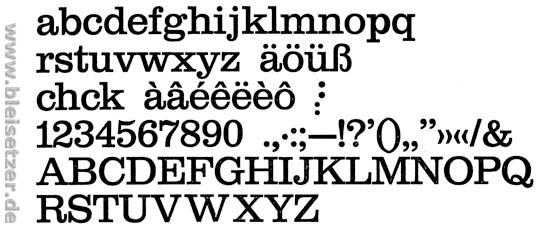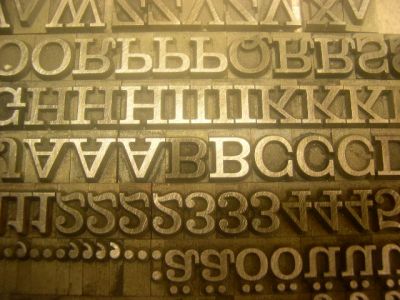
ich muss eine sehr umfangreiche Arbeit über die Schriftart Clarendon erstellen, über ein Brainstorming zu Clarendon würde ich mich sehr freuen. :)
• Schrifthersteller- Benjamin Fox ( Herrmann Eidenbenz hat sie dann für Linotype umgesetzt)[/*:m:3dcp7vno]
• Serifen sind rechtwinklig, die Strichstärke (linear)[/*:m:3dcp7vno]
• Haar- und Grundstriche sind unterschiedlich ausgeprägt, Tropfenartige Formung der Abstriche, Vertikaler Verlauf der Schriftachsen bei Rundformen[/*:m:3dcp7vno]
• Literatur: Schriften erkennen Von Daniel Sauthoff, Anatomy of a Typeface Von Alexander S. Lawson[/*:m:3dcp7vno]
Gruppe V - Serifenbetonte Linear-Antiqua - Clarendon
D. Stempel AG, Frankfurt am Main
Erstguß 1953
Hermann Eidenbenz
Originalerzeugnis der Haas'schen Schriftgießerei AG, Münchenstein, Schweiz.
1963 dann von der Stempel AG übernommen.
Hermann Eidenbenz war der Entwerfer. Geboren in Basel am 4.9.1902. Er war hauptberuflich Graphiker, beschäftigt bei der Reemtsma Zigarettenfabrik in Hamburg.
Die Photos zeigen einen kompletten Zeichensatz der Bleisatz-Version.
Nach meinen Informationen ist die Clarendon weitaus älter. Bei mir wird sie auf das Jahr 1845 datiert, entworfen von Robert Besley.
Die Über- bzw. Ausarbeitung übernahm dann 1953 Hermann Eidenbenz.
Nach meinen Informationen ist die Clarendon weitaus älter. Bei mir wird sie auf das Jahr 1845 datiert, entworfen von Robert Besley.
Die Über- bzw. Ausarbeitung übernahm dann 1953 Hermann Eidenbenz.
Ich dachte Vincent figgins war der erste 1815?
In dem Buch was hier habe steht, dass Robert Besley eine Firma hatte R.Bensley & Co., und dort sein Partner Benjamin Fox Clarendon geschnitten/entworfen hat.
Ich habe ein Problem zu verstehen/herauszufinden was Herrmann Eidenbenz konkret gemacht hat, hat er den Bleisatz dann 1965 für Clarendon erstellt, weil es vorher keine gab?
Ach und Stefan woher hast du dieses Photos, dass denn kompletten Bleisatz-Version zeigt?
Sicher hat Ralf recht, wenn er schreibt, daß die Clarendon 1845 entworfen wurde. Das mag sein.
Aber gab es denn damals schon "industriell nutzbaren Bleisatz"?
Gab es überhaupt schon genormte Lettern, die ja Grundvoraussetzung für ein Aufblühen der Graphischen Industrie waren?
Ich habe immer ein leichtes Problem damit, wenn Schriften immer weiter zurückgeführt werden bis auf einen Ursprung, der im Vorindustriellen beginnt. Denn dann muß man doch auch fragen: Woher hatte denn der Entwerfer 1845 seine Inspiration? Worauf bezog er sich. Ja, ich kenne die Geschichte der Egyptienne-Schriften. Theoretisch kann man so eine jede Schrift zurückführen auf Keilschriften u.ä.
Für mich persönlich beginnt die Neuzeit einer Schrift in dem Moment, in dem sie von einer Schriftgießerei für einen professionellen Einsatz angeboten wird. Die Information über deren Wurzeln gehören für mich selbstverständlich als wichtiges Hintergrundmaterial dazu, aber wichtig sind für mich vor allem die von mir genannten Daten der Stempel AG.
Nein, ich sehe dies nicht zwingend im Widerspruch zu Ralf.
Sicher hat Ralf recht, wenn er schreibt, daß die Clarendon 1845 entworfen wurde. Das mag sein.
Aber gab es denn damals schon "industriell nutzbaren Bleisatz"?
Gab es überhaupt schon genormte Lettern, die ja Grundvoraussetzung für ein Aufblühen der Graphischen Industrie waren?
Ich habe immer ein leichtes Problem damit, wenn Schriften immer weiter zurückgeführt werden bis auf einen Ursprung, der im Vorindustriellen beginnt. Denn dann muß man doch auch fragen: Woher hatte denn der Entwerfer 1845 seine Inspiration? Worauf bezog er sich. Ja, ich kenne die Geschichte der Egyptienne-Schriften. Theoretisch kann man so eine jede Schrift zurückführen auf Keilschriften u.ä.
Für mich persönlich beginnt die Neuzeit einer Schrift in dem Moment, in dem sie von einer Schriftgießerei für einen professionellen Einsatz angeboten wird. Die Information über deren Wurzeln gehören für mich selbstverständlich als wichtiges Hintergrundmaterial dazu, aber wichtig sind für mich vor allem die von mir genannten Daten der Stempel AG.
Nein, ich sehe dies nicht zwingend im Widerspruch zu Ralf.
Ergänzung:
Bestes Beispiel ist doch die Helvetica.
Wann wurde sie geschaffen? 1937, als Max Miedinger die ersten Entwürfe machte? In den 50er Jahren, als Haas sie unter einem anderen Namen erstmals herausgab? In den 60er Jahren, als Stempel sie übernahm und unter dem Namen Helvetica vermarktete?
Liegt ihr Ursprung nicht auch in der "Grotesken"? Also in anderen Schriften gleicher Art, wie z.B. der AG? Wäre damit der Ursprung mit demselben Recht nicht noch weiter vorzuverlegen?
Miedinger hat 1937 keine Entwürfe für die Helvetica, bzw. Neue Haas Grotesk gemacht. Diese irreführende Info von dir basiert sich auf einem Tippfehler. Es stimmt einfach nicht, und ich habe das dir schon gesagt! Wieso schreibst du das immer wieder? :(
ich habe gefunden dass die Clarendon von Starbucks verwendet wird/wurde, leider kann ich keine Beispiele dafür finden.
Sie soll auch die Hausschrift von U2 sein (in einem der Forumbeiträge gelesen), bildbeispiele dafür finden konnt ich aber nicht.